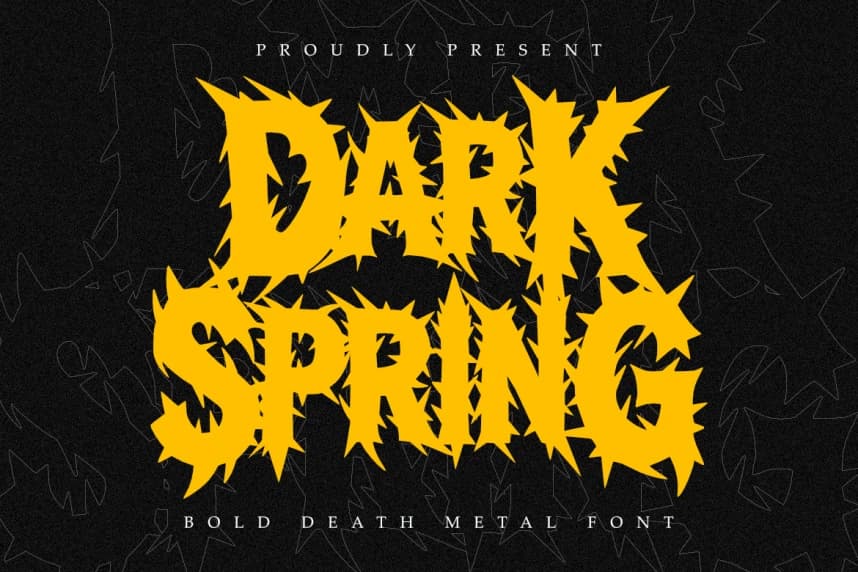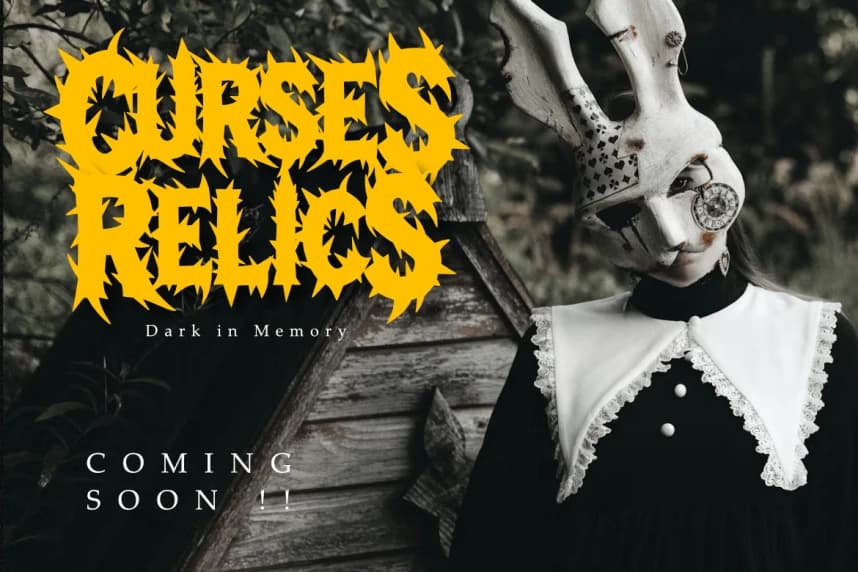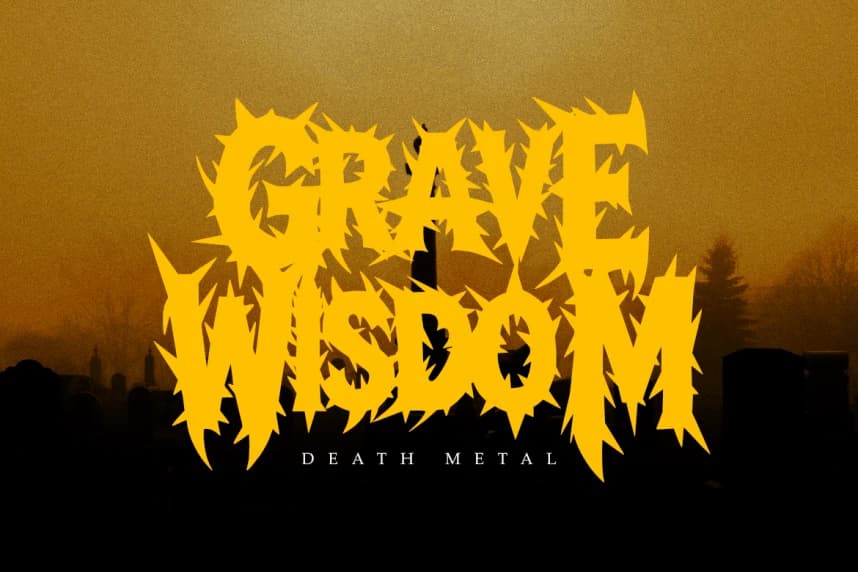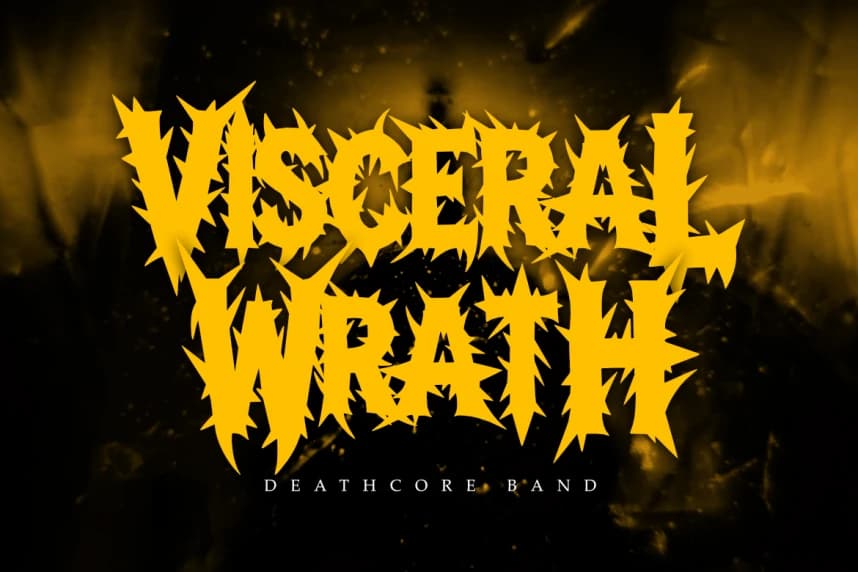
Dark Spring Font, sofistike markalaşma ve üst düzey uç tasarım projeleri için tasarlanmış sert ve profesyonel bir yazı tipidir. Keskin ve agresif harf formları çağdaş bir his ile zamansız bir etki sunar.
Dark Spring Font, sofistike marka kimliği ve üst düzey uç tasarım projeleri için tasarlanmış sert bir profesyonel yazı tipidir. Keskin ve agresif harf biçimleri çağdaş bir his ile zamansız bir görünüm sağlar.
Dark Spring Font, sofistike markalaşma ve üst düzey uç tasarım projeleri için tasarlanmış sert ve profesyonel bir yazı tipidir. Keskin ve agresif harf formları çağdaş bir his ile zamansız bir etki sunar.
Dark Spring Font, sofistike marka kimliği ve üst düzey uç tasarım projeleri için tasarlanmış sert bir profesyonel yazı tipidir. Keskin ve agresif harf biçimleri çağdaş bir his ile zamansız bir görünüm sağlar.